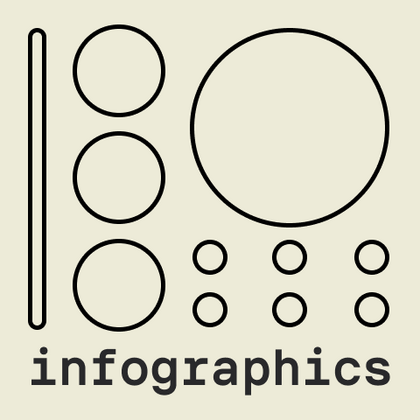
Шрифты для инфографики
Особый класс типографических решений представляют собой шрифты для инфографики, где каждая деталь подчинена задаче эффективной передачи информации. В каталоге TypeType собраны гарнитуры, которые превращают сухие данные в выразительные визуальные образы. Эти шрифты отличаются адаптивными характеристиками — они сохраняют четкость как в печатных отчетах, так и в цифровых презентациях. Особенностью таких гарнитур является их универсальность: они одинаково хорошо работают с цифрами, текстом и специальными символами. Профессиональная оптимизация обеспечивает комфортное восприятие информации независимо от формата ее представления. Такие гарнитуры от TypeType — это инструмент, который помогает данным обрести ясную и запоминающуюся форму.
TT Polihaus — экспериментальный гротеск, который на первый взгляд кажется обычным, а затем разбирается на части, превращаясь в трафаретный узор.
TT Odellia — старостильная антиква с современным рисунком, вдохновлённая венецианскими шрифтами и классической музыкой.
TT Rationalist — функциональный и оригинальный брусковый шрифт с актуальным рисунком. Он универсален и подходит как для заголовков, так и для массивов текста.
TT Turns — геометрический гротеск с акцентными круглыми знаками и выразительными нависающими элементами. Это универсальный шрифт, который лаконично выглядит и отлично читается в маленьком размере, при этом в крупных кеглях становится акцидентным и проявляет свой характер на максимум. Он энергичный, сильный и динамичный — особенно отчётливо это проявляется в наклонных начертаниях.
TT Quaris — изысканная и современная ленточная антиква. Перед разработкой этой гарнитуры мы провели глубокое исследование архетипов ленточных антикв.
TT Modernoir — акцидентный гротеск с разноширинными пропорциями. Плавные линии и изящные формы ар-нуво в этом шрифте сочетаются с ритмичностью и импровизационной свободой джаза.
TT Moons — узкая и контрастная антиква. Данное шрифтовое семейство очень элегантно работает в классических темах дизайна. TT Moons по стилистике относится к глиптальным новостильным шрифтам. Идеальная сфера использования TT Moons — это верстка журналов, книг и газет.
TT Fellows — гуманистический гротеск с механистическими мотивами. Открытые формы, дружелюбно-нейтральный характер тонких весов и ещё более мягкий характер в жирных начертаниях.
TT Interphases Pro — неогротеск, который создавался специально для работы в интерфейсах. Среди визуальных особенностей TT Interphases Pro — плавные формы скруглений, повторяющиеся во всех элементах: благодаря им большие массивы текста читаются легко и приятно.
TT Gertika — геометрический гротеск с динамичным характером и танцующим ритмом. Идея шрифта зародилась из леттеринга на американском плакате второй половины 30-х годов.
TT Biersal — акцидентный гротеск со свободным, озорным и авантюрным характером. Отправной точкой для его создания послужил немецкий плакат начала 30-х годов. Мы хотели сохранить не только пропорции, но и ощущение небрежности, живости леттеринга из референса.
TT Paplane — акцидентный сквадраченный гротеск. Так, характерные черты этого гротеска — сквадраченные формы, 45-градусные срезы и обтекаемые внешние контуры.
TT Octosquares — октагональный гротеск с футуристическим характером. Этот шрифт отличается геометричностью и своеобразной «мозаичностью»: он как бы собран из отдельных фрагментов, что проявляется и в мельчайших деталях.
TT Carvist — современный экспериментальный гротеск со сверхузкими пропорциями. Название гарнитуры отсылает к резьбе по камню: характерные черты этого шрифта — геометричность и брутальность.
TT Firs Text создавался на основе обновленной в 2023 году гарнитуры TT Firs Neue. Мы сохранили эстетику скандинавского минимализма, но полностью перерисовали все выразительные элементы, сделав их более мягкими и традиционными.
TT Lakes Neue в версии 2.0 — продолжение геометрического гротеска, вдохновлённого финским функционализмом. Новая версия предоставляет больше возможностей, ведь мы не только увеличили кассовый состав и улучшили шрифт технически, но и доработали его визуальный характер.